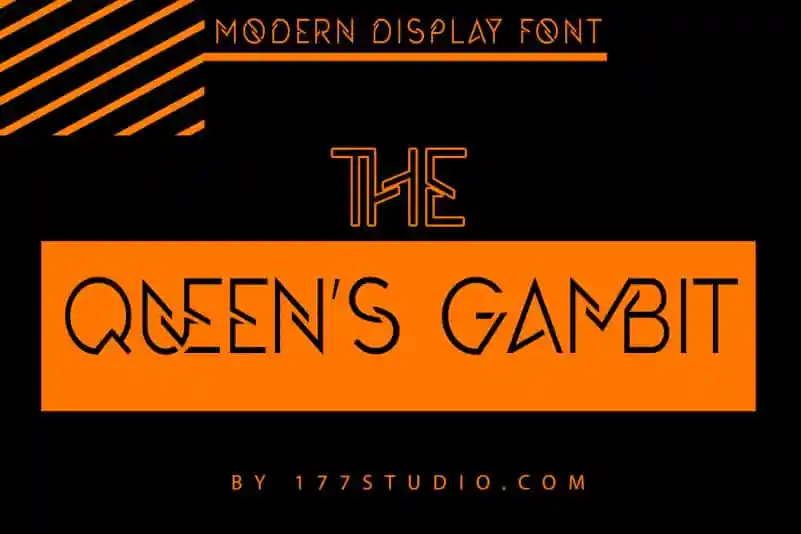
A The Queen’s Gambit Font é uma escolha excepcional para quem busca um gosto único e moderno no design. Desenvolvida pela 177Studio, essa tipografia de destaque abraça formas geométricas modernas e não convencionais. O resultado? Uma fonte que traz originalidade à sua identidade visual, tornando suas criações mais chamativas. Ideal para uma ampla gama de aplicabilidades, a The Queen’s Gambit Font é perfeita para projetos inovadores como ambientes futuristas em jogos de videogame retro, revistas e cartões postais. Além disso, ela se destaca também para criações que requerem uma identidade forte e diferenciada, como logotipos, projetos DIY e cartas de convite. Em suma, a The Queen’s Gambit Font é um recurso indispensável para designers criativos buscando dar um toque moderno e inovador a seus trabalhos.